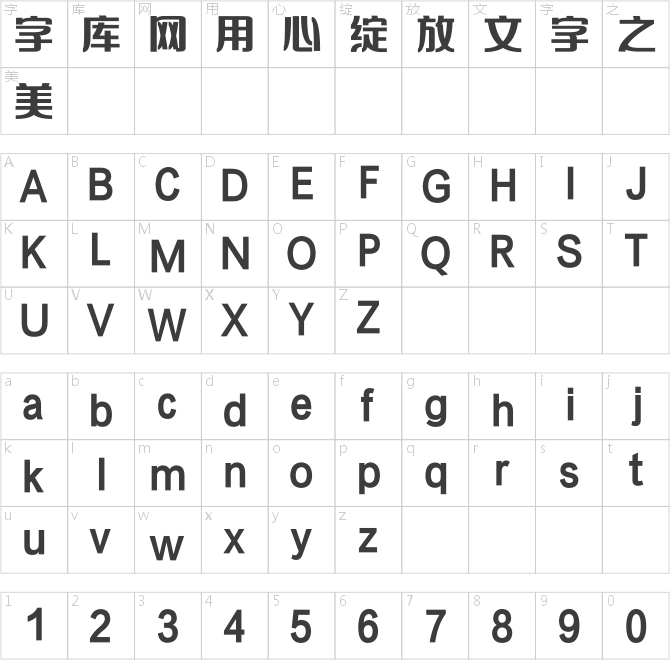
方正蘇新詩(shī)藝標(biāo)簡(jiǎn)體 詳情頁(yè)
方正蘇新詩(shī)藝標(biāo)
綜藝
方正蘇新詩(shī)藝標(biāo)簡(jiǎn)體字體字庫(kù)是一款讓人賞心悅目、百看不厭的中文字體,適合各類廣告和產(chǎn)品包裝設(shè)計(jì)應(yīng)用,字體大小1.76MB,格式為ttf字體,上傳用戶是woslxn,作者/版權(quán)方為方正字庫(kù)